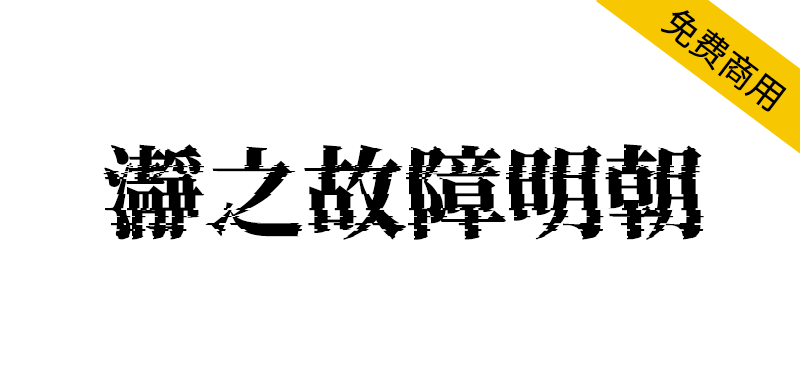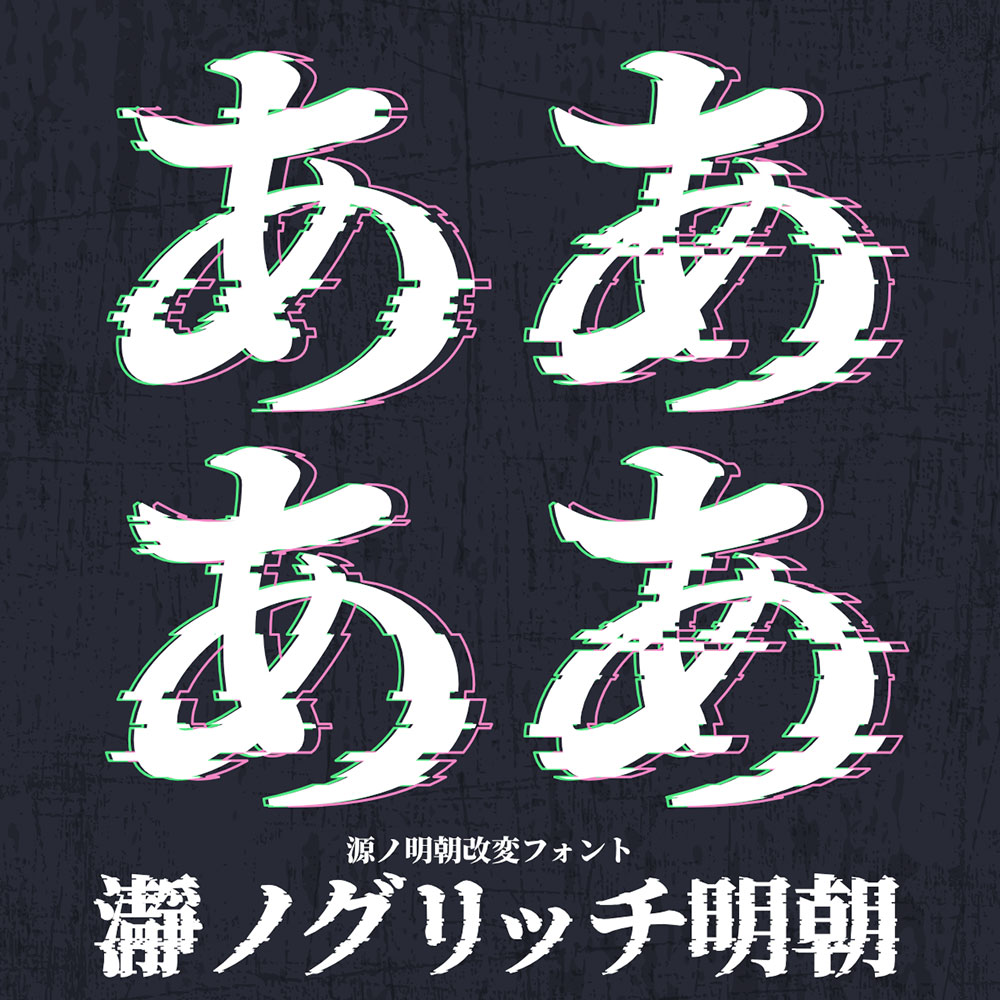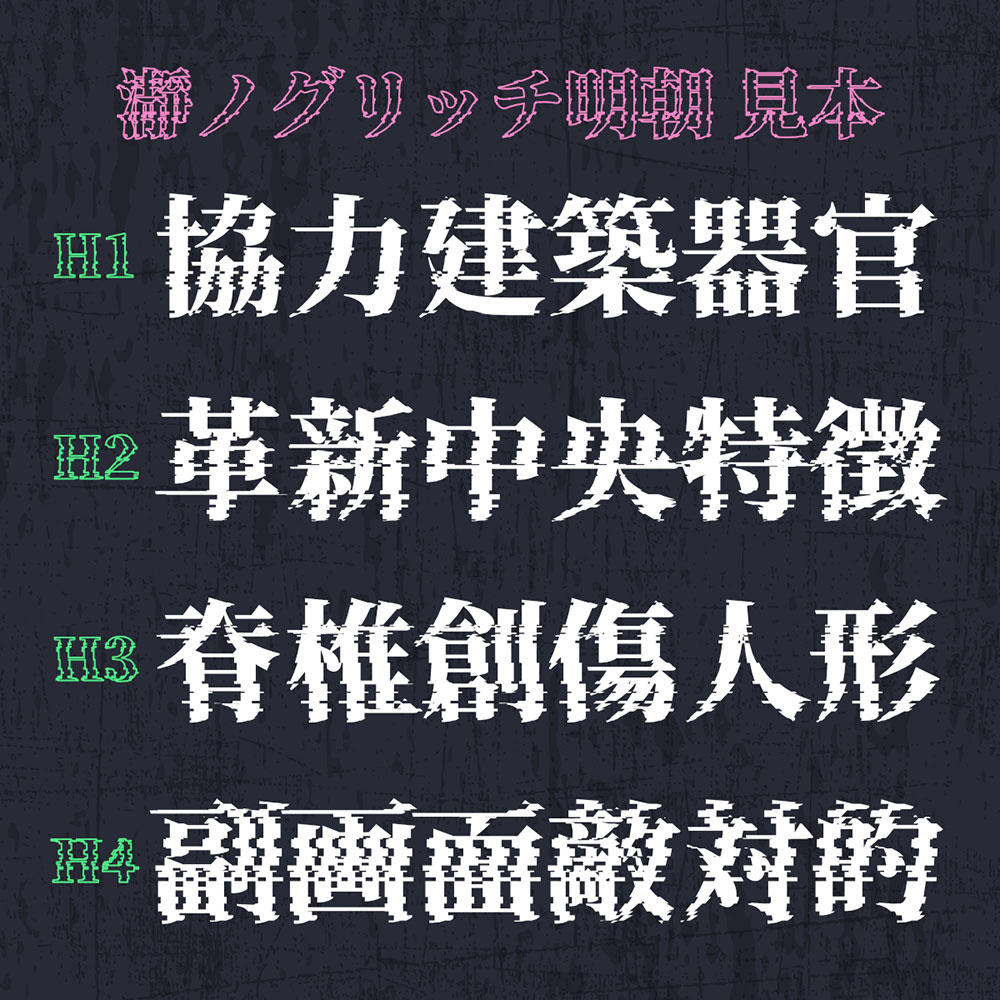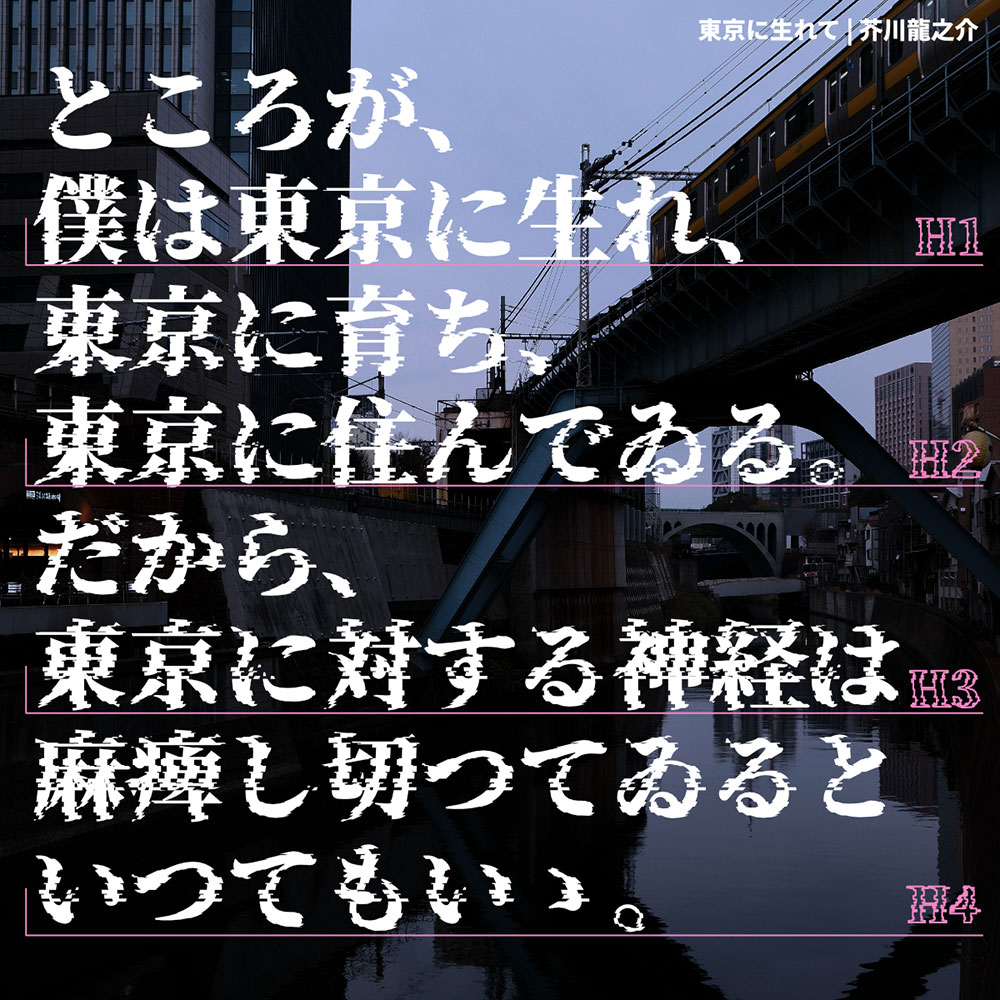
【瀞之故障明朝】基于思源宋体制作的故障特效字体
厌倦了千篇一律的传统宋体?瀞之故障明朝(瀞ノグリッチ明朝)将思源宋体注入故障艺术,创造出令人惊艳的视觉冲击——笔画粗黑、断裂错位、像素重影,完美模拟数字信号干扰的独特质感!这款字体基于Adobe-Japan1-6标准(部分字符可能缺失),并遵循S字体协议,完全免费商用、可自由修改和再分发。本文揭秘了字体的设计细节、使用许可和获取来源,助你轻松为设计项目增添前卫风格。立即阅读,掌握这款颠覆常规的字体神器!
【瀞之故障明朝】基于思源宋体制作的故障特效字体
瀞之故障明朝(瀞ノグリッチ明朝)是一款基于思源宋体进行艺术处理,加工成具有故障特效的宋体字体,遵循Adobe-Japan1-6标准(部分字符可能存在缺失),依据SIL OPEN FONT LICENSE Version 1.1协议授权发布,可商用、可自由再分发、修改。
【瀞之故障明朝】基于思源宋体制作的故障特效字体